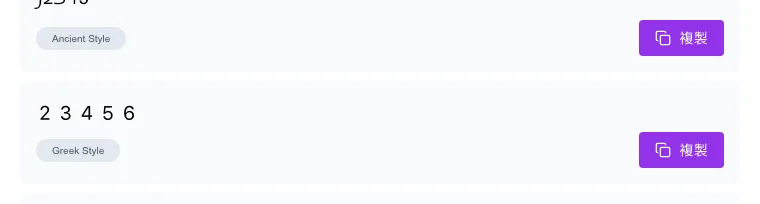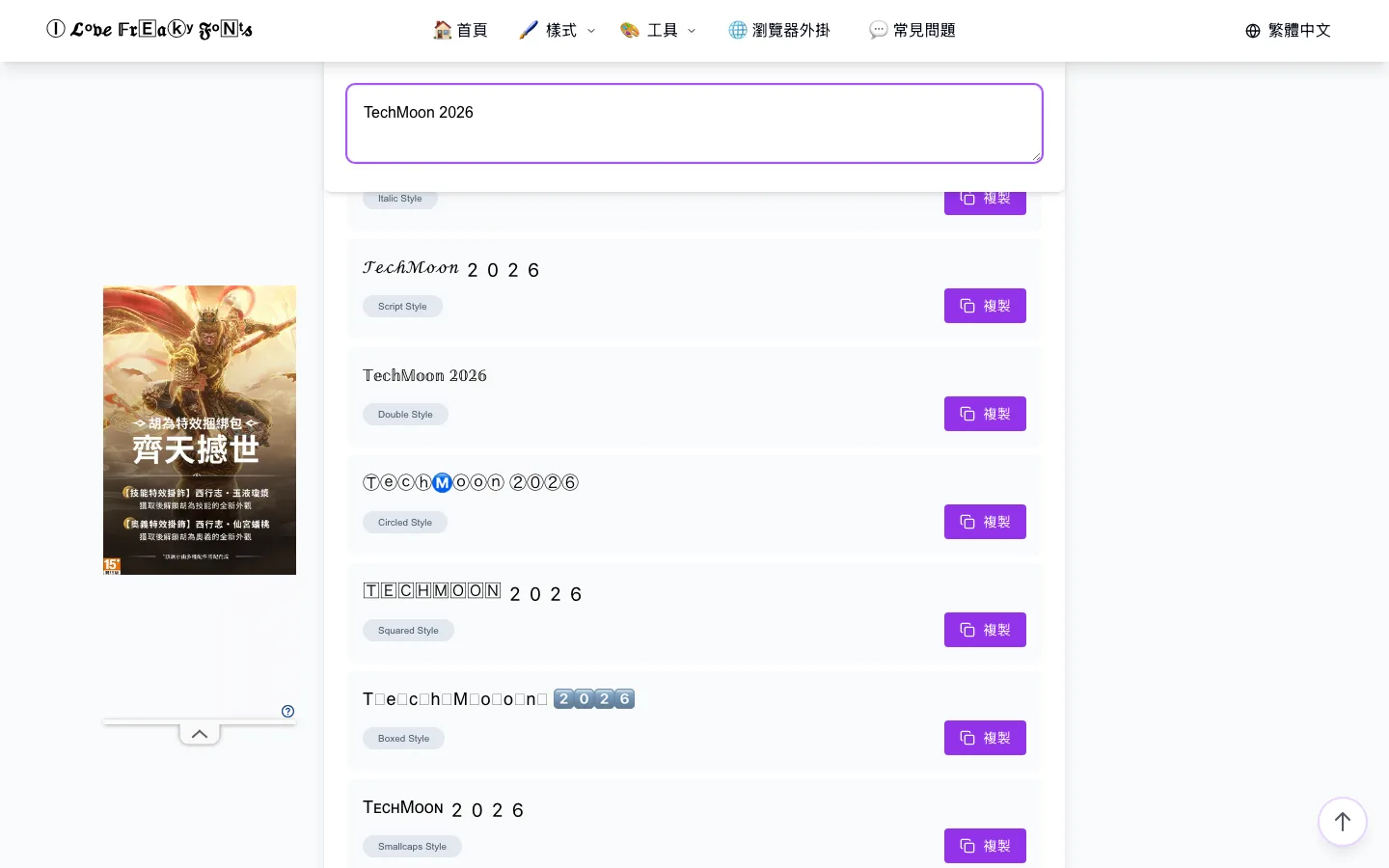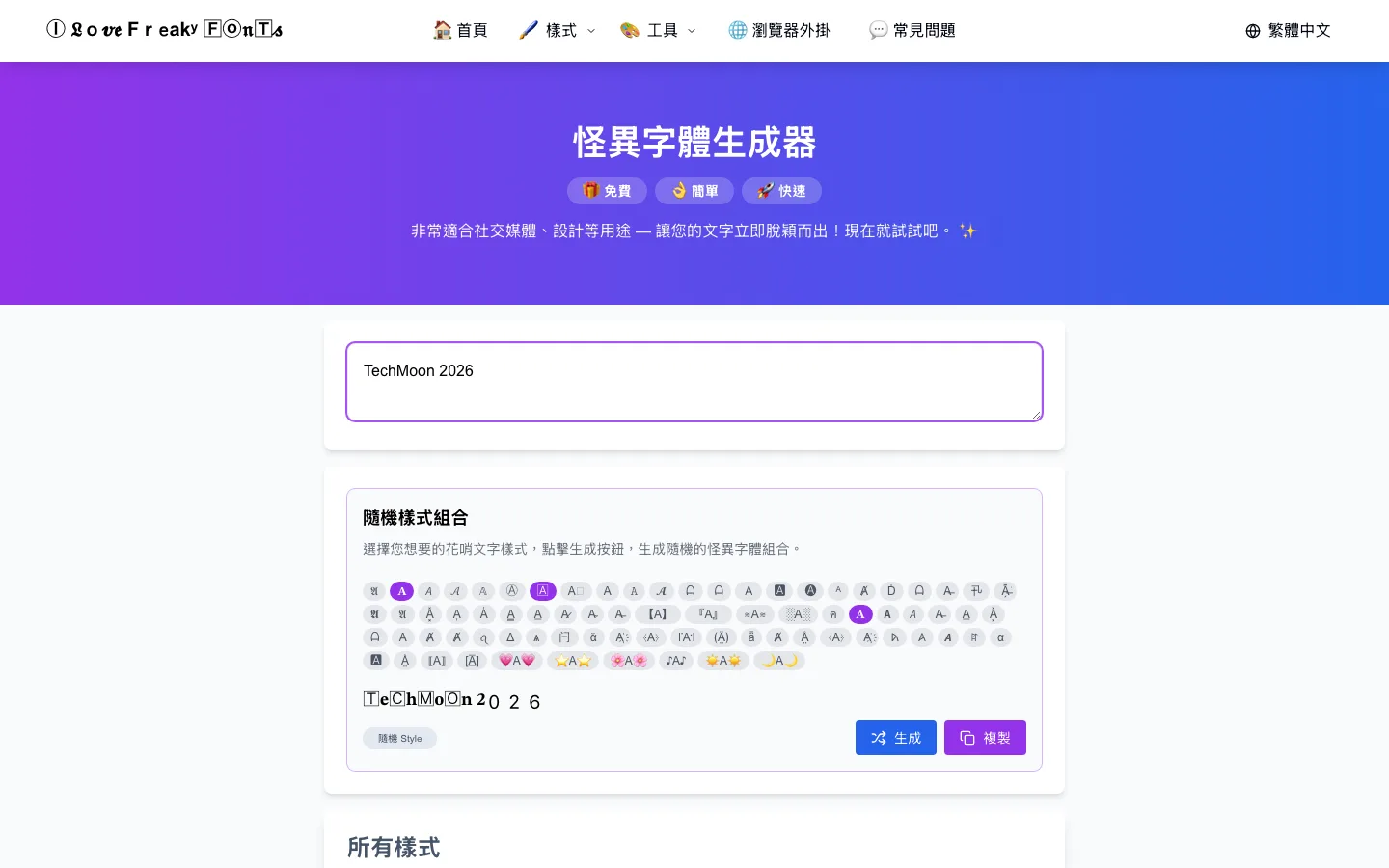
Freaky Fonts 免費怪異字體產生器:把英數文字變成 Unicode 造型
Freaky Fonts 是免費線上怪異字體產生器,把英數文字即時換成 77 種 Unicode 造型,複製即可貼進 IG、TikTok 等社群。實測轉換全程在瀏覽器內完成、文字不外送,但希臘風格會把數字悄悄加一,中文與標點完全不受影響,貼出去前務必逐字核對數字。
Freaky Fonts 是一個免費、免安裝、打完字馬上出結果的線上怪異字體產生器,輸入英文和數字,頁面立刻列出幾十種造型變化,點一下複製就能貼進 Instagram 簡介、TikTok 暱稱或 YouTube 標題。我實際打開繁中介面輸入文字測試:轉換全程在瀏覽器裡完成,打什麼字不會送到伺服器,複製鈕也真的把造型文字放進了剪貼簿。免費、文字不出瀏覽器、即時,這三件事都成立。
不過在你把結果貼出去之前,有三件事值得先知道:有一種樣式會把你的數字悄悄加一,輸入 12345 複製到的是 23456;中文字完全不受影響,這是只服務英數字的工具;官方說有超過一百種樣式,我在頁面上逐一數出來是 77 種。
它換的不是字體,是文字底下的代碼點
先講清楚這類工具的原理,因為它決定了所有優點和缺點。Freaky Fonts 並沒有載入任何字型檔,它是把你自己打的每個字母,換成一個長得很不一樣的 Unicode 字元。大寫 A 可以變成數學字母區的 𝔄、圓圈裡的 Ⓐ、方框裡的 🅰,數字 1 可以變成 𝟏 或 ①。對電腦來說,這些都是實實在在的不同字元,跟原本的 A 和 1 是兩回事。
這個原理帶來最大的好處:貼到哪裡都有效。因為輸出的是普通文字,不是圖片也不是特殊格式,所以任何接受純文字輸入的欄位都吃,Instagram 簡介、TikTok 暱稱、WhatsApp 狀態、Discord 頻道名稱都不需要對方平台做任何支援。站方的常見問題也是這樣宣稱的,並列舉了 TikTok、Facebook、YouTube、Twitter、Instagram、WhatsApp 這些平台。
樣式的變化手段大致兩類。多數樣式做一對一替換,每個字母換一個造型字元;少數樣式再疊上組合附加符號,把斜線、波浪、點綴一層層壓到字母上,故障風格就是這樣疊出來的,輸出看起來像字母長了藤蔓,疊得高的樣式在某些環境有機會把行高撐開、讓排版跑掉。
代價同樣來自這個原理。字型檔缺字的裝置上,造型字元會顯示成方框或問號,這點站方在常見問題裡自己承認,而我實測時就親眼看到:部分樣式的輸出在我這台一般桌機的瀏覽器裡直接顯示成方框,連站方自己都沒辦法保證每個樣式在每台裝置上活得下來。另外兩個衍生問題值得放在心裡:造型字元和原字母在檢索系統裡是不同字串,別人用正常拼法搜尋時對不上你;對螢幕閱讀器來說,這串字元幾乎不可讀,公共帳號或商業帳號用它等於放棄一部分可及性。
我輸了三組文字,有一組的數字回來時加了一
實測分三組:純英文加數字、純中文、純數字。前兩組大致如預期,第三組挖出了這個工具最需要警惕的問題。
輸入 TechMoon 2026 時,頁面即時列出全部樣式卡的轉換結果,粗體、斜體、手寫體、圓圈體、哥德體一路排下去,反應速度快到沒有等待感。操作上只有一個輸入框,打字時固定樣式卡全部同步更新,不需要按任何確認鈕;唯一要按產生鈕的是最上面的隨機樣式卡,每按一次重擲一輪組合。這裡能確認兩件事:轉換是純前端做的,打字過程中頁面對外發出的請求只有廣告和流量統計,文字內容本身沒有離開瀏覽器;複製鈕可用,點下去剪貼簿裡就是造型文字。隨機樣式卡還能把不同造型混在同一個字串裡,不同字母會混用不同造型。
Freaky Fonts 繁體中文首頁,輸入英數文字後隨機樣式卡顯示造型文字轉換結果Pin
繁中介面與隨機樣式卡:輸入即時更新,按產生鈕重擲組合(TechMoon 實測截圖)
純數字組就出事了。輸入 12345,往下滑到希臘風格那張卡片,畫面上顯示的轉換結果是 23456,每一位數字都被加了一。換輸入 abc123,字母也被推了一位,輸出變成 в¢∂234,等於把 bcd 和位移後的數字用西里爾字母與符號拼出來。這個結果會真的進剪貼簿:複製下來的就是 23456。更糟的是 0 會直接消失,輸入 890 複製到的是 91,位數都變短了。也就是說,如果你把電話號碼、價格、日期或優惠碼交給這個樣式,貼出去的數字是錯的,而且錯得非常安靜。
希臘風格樣式卡將輸入的 12345 轉換成 23456 的實測畫面Pin
希臘風格實測:輸入 12345,頁面顯示 23456,每位數字都被加一(TechMoon 實測截圖)
更麻煩的是行為不一致。同樣輸入 12345,手寫體和斜體讓數字原樣通過,圓圈體轉成 ①②③④⑤,按鍵體轉成 1️⃣2️⃣3️⃣4️⃣5️⃣,上標體轉成 ¹²³⁴⁵,遠古體換成一排你認不出來的字元,希臘風格卻直接把值改掉。77 張樣式卡對數字的處理方式各行其是,你沒辦法建立數字不會被動的信任,只能每次貼出去之前逐字核對。隨機樣式卡也一樣,它把不同造型混進同一個字串,我複製到的結果裡同一組數字有的變有的沒變,隨機等於不可預期。
多張樣式卡並列顯示不同轉換結果,部分造型字元在瀏覽器中呈現為方框Pin
樣式卡與實際輸出:部分造型字元在桌機瀏覽器直接顯示成方框(TechMoon 實測截圖)
講到數量。官方常見問題寫超過一百種樣式並且每天都在增加,我在繁中首頁逐一數了複製鈕,固定樣式卡是 77 張,再逛完十一個分類頁做交叉比對,聯集還是 77。以現場數字為準,宣稱數字灌了約三成。77 種對多數人夠用了,但破百和近八十是兩種印象,這類行銷數字你以後看到可以先打折。
中文原樣進原樣出,這是英數限定工具
第二組測試輸入「科技月球 ABC 123」,結果只有 ABC 和數字起了變化,中文字原封不動。再把純中文丟進去,所有樣式卡的轉換結果直接留白。標點符號和空格同樣不會被轉換,所以中英混雜的句子貼出去,會是英文變造型、中文與標點照舊的混合畫面。這條邊界是官方明文寫死的:官網瀏覽器擴充功能的常見問題自己寫明,支援範圍是拉丁字母 A 到 Z 和阿拉伯數字 0 到 9,其他字元包含標點、符號和非拉丁文字都保持原樣。站方在這件事上很誠實,只是首頁宣傳不會特別告訴你。
這條邊界直接決定這工具跟你有沒有關係。想讓中文暱稱變花俏的,這個工具幫不上忙,因為 Unicode 裡根本不存在成套的中文字造型替身。你的替代路線是換字型而不是換字元:看本機已安裝字型的實際預覽可以參考 FontShow 本地字型預覽工具,要書法感的文字可以看 線上書法字體產生器 的整理。
介面本身倒是親切。網站提供十七種語言,導覽列的語言選單和頁尾連結都能切換,繁中介面完整,選單、說明、按鈕全是繁體中文,輸入英文數字後每張樣式卡即時更新,使用上零障礙。
站內還有六個小工具,和一枚幾乎沒人裝的擴充
除了主產生器,網站附了六個小工具:隨機樣式組合、故障文字產生器、自訂字元映射、文字分隔符插入、文字反轉、隨機文字。都是同一套代碼點替換的變形應用,其中自訂字元映射比較有意思,讓你自己定義每個字母要換成什麼字元,等於手工打造專屬樣式,其餘幾個用得上就順手開,單獨不值得專程前往。順帶一提,站方連自己頁面頂端的站名都是用造型文字拼出來的,算是這套玩法最直接的展示。
瀏覽器擴充 Freaky Page 比較特別,它能把目前逛的任何網頁裡的英數文字一鍵換成造型字體,讀的寫的都能變。方向有趣,採用度很低:Chrome 線上應用程式商店顯示 22 位使用者、7 則評分、版本停在 1.0,最後更新 2025 年 2 月。把整個網頁文字變成頁內搜尋找不到、不利朗讀的狀態,娛樂性質居多,正式場合別開。
貼上社群前的三個檢查點
綜合實測,把這工具用得安心只要記住幾件事。
數字要逐字核對。希臘風格會把數字加一,0 還會直接消失,其他樣式對數字的處理也不一致,任何含數字的內容貼出去前自己讀一遍,這是最可能出錯的地方。接著先在目標平台試貼一則。造型字元在不同裝置的顯示結果不一,我這台桌機瀏覽器就有樣式直接顯示成方框,先用小貼文或限動測試,確認你要的樣式在追蹤者手機上活得下來。公共與商業帳號則要降級使用。造型文字在檢索系統裡對不上原字母,對螢幕閱讀器也近乎不可讀,個人帳號玩造型無妨,拿來當品牌主要名稱就是拿能見度換裝飾。
開始使用不用三分鐘:打開網站切到繁中介面,在輸入框打英文或數字,從樣式卡挑一個順眼的按複製,貼到目的地就完成了。沒有帳號、沒有安裝,頁面上也看不到用量限制。
我的判斷:如果你要在英文社群做個人風格,暱稱、簡介、頻道標題想跟別人不一樣,Freaky Fonts 是即開即用的免費選擇,記得核對數字就好。需求是中文字、品牌命名或正式用途的,這個工具到不了你要的地方,往字型和設計工具的方向走會更實際。